Zeichenabstand
Unter »Zeichenabstand« wird der linke und rechte Abstand von benachbarten Buchstaben, Arabischen Ziffern und Schriftzeichen verstanden; ugs. Buchstabenabstand.
Neben künstlerischen Ambitionen hat die Zurichtung von Zeichenabständen einer maschinell oder digital reproduzierbaren Schrift Einfluß auf die Schriftästhetik, den Grauwert und die Lesbarkeit einer Schrift bzw. eines Textes.
Wird der Abstand zwischen zwei Schriftzeichen, beispielsweise bei kritischen »Kerning-Paaren« bzw. »Unterschneidungspaaren« (z.B. AV, Ty oder yo) beschrieben, spricht man von Zeichenabstand. Wird der gleichmäßige Abstand zwischen mehreren bzw. allen Schriftzeichen einer Textpassage beschrieben, spricht man von Schriftlaufweite.
Zeichenabstände werden in der Typografie in der relativen Maßeinheit Geviert gemessen.
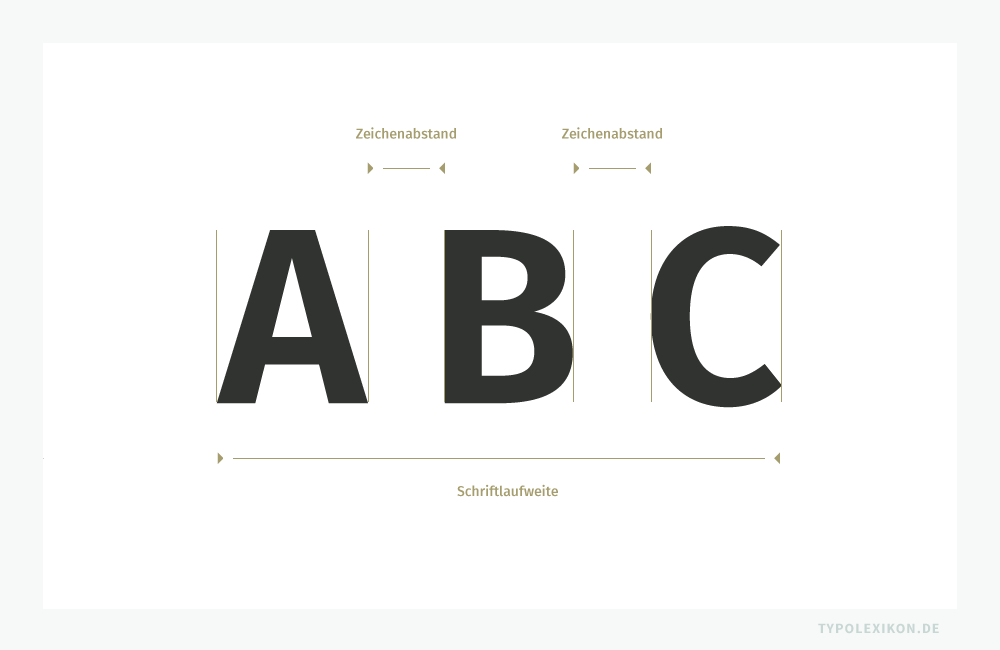
Die Zeichenabstände bei Proportionalschriften sind unterschiedlich, bei dicktengleichen Schriften (Monospace) in der Regel optisch gleich groß. Bei OpenType® Fonts werden die Zeichenabstände durch das Zeichenabstand-Kerning vorgegeben. Darüber hinaus können Zeichenabstände in Desktop Publishing Computerprogrammen, beispielsweise InDesign® von Adobe® 1) oder QuarkXpress® von Quark®, 2) individuell oder systematisch durch eine positive (Spationierung (+LW)) oder negative (Unterschneidung (-LW)) Laufweitenveränderung der Normalschriftweite (LW 0) verändert werden.
In Büro- und Textverarbeitungsprogrammen, z.B. Microsoft Word®, ist das Ändern einzelner Zeichenabstände nicht oder wenn ja, dann nur sehr marginal möglich. 3) Das Verändern von einzelnen Zeichenabständen in einer Website mittels CSS Cascading Style Sheets 4) ist nicht oder nur mit sehr viel Aufwand möglich.